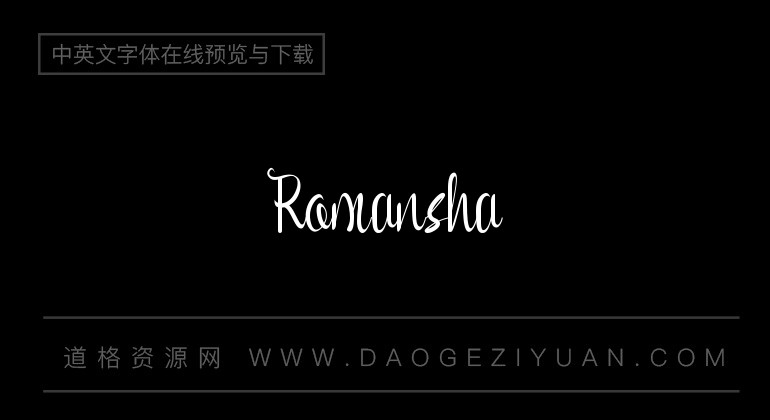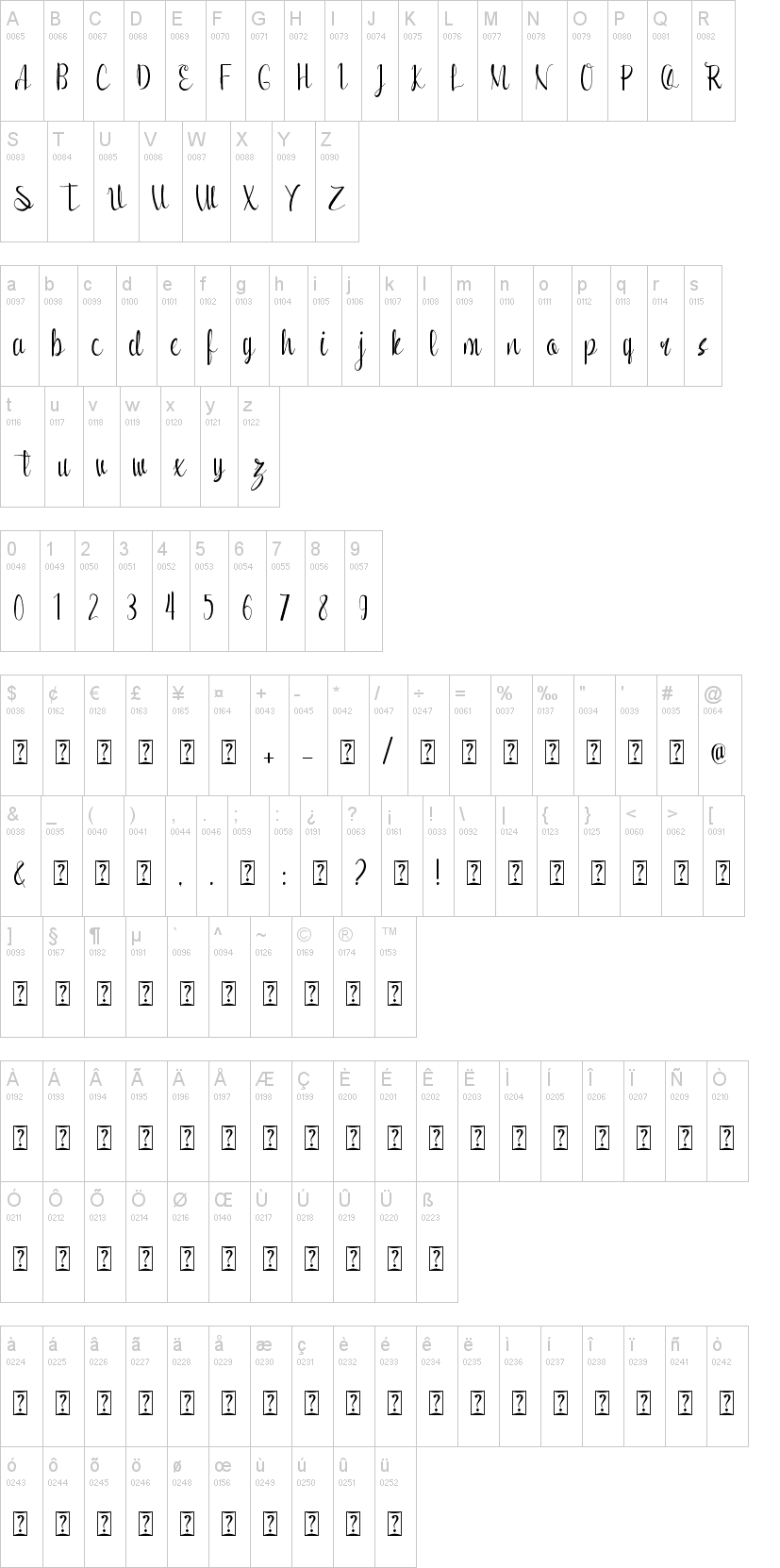
Romansha 是一种英文字体,它结合了罗马和沙特阿拉伯风格,在罗马和沙特阿拉伯文字之间创造了一种新的英文字体。它具有独特的线条结构,拥有清晰的曲线,优雅的轮廓,以及舒适的字体体积。它还具有精细的细节,使得它可以被用于印刷,网页和设计的场景。内容介绍
Romansha是一款非常不错的手写艺术字体,具有很好的视觉感,适合于文化类的宣传设计、商业类品牌的广告和产品包装设计以及个性化文字排版等较多场景。